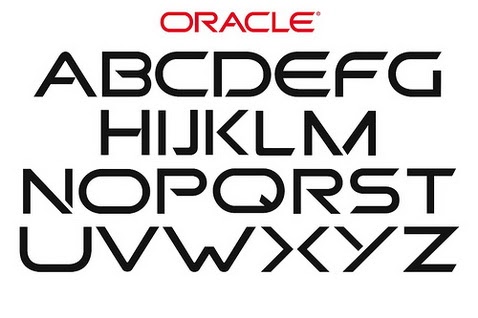
В формировании корпоративного стиля, призванного создавать образ компании, шрифт играет одну из самых заметных ролей. Он является центральным связующим элементом, упрощает и поддерживает использование логотипа, сетки и установленных правил оформления документов. Характерная форма букв шрифта фиксируется в подсознании и формирует уникальный образ компании. Шрифт, особенно эксклюзивный, может служить своеобразной «скрытой рекламой» продукции вашей компании: он приводит к устойчивым ассоциациям, так же, как секундные отрывки ярких рекламных видеороликов. Есть классические шрифты, подходящие для рекламы дорогих украшений, консервативные, на которые обратят внимание приверженцы традиций, демократичные шрифты, наиболее пригодные для рекламы молодежных и детских товаров, и национальные, призванные подчеркнуть народные традиции. Профессионально спроектированные шрифты хорошо работают во всех средах коммуникации от часов до билбордов. Еще одна функция шрифта — помощь в общении с вашими партнерами по бизнесу.
Предустановленные в приложениях компании Microsoft шрифты Arial и Times New Roman стали фактически стандартом современной коммуникации. С одной стороны это упростило перенос документов с одного устройства на другое, с другой — привело к обезличиванию текстов. Чтобы вас заметили на сегодняшнем конкурентном рынке подбор правильного шрифта не менее важен, чем создание логотипа.
Успешность коммуникации бренда с потребителем определяется его присутствием во всем многообразии медийных сред от рекламных щитов на магистралях до мобильных приложений на часах клиента. Непрерывность взаимодействия с потребителем — основа развития в этом быстро меняющемся мире.
Клиенты, особенно молодые, технологически грамотные, ожидают увидеть ваш бренд на нескольких платформах, что позволяет легко взаимодействовать с ним по своему усмотрению. По данным Google, 65 процентов потребителей начинают онлайн-операции на одном устройстве, а продолжают на другом. Сегодня текст и шрифт более важны для бренда, чем когда-либо, а использование последовательной типографии становится основным и самым простым способом установить ту самую непрерывность.
Леттеринг — это создание уникальной надписи, в которой каждая буква чаще всего создается в несколько приемов и с использованием нескольких инструментов. Неоновая вывеска, меню на грифельной доске ресторана или вылепленные годы постройки здания на фасаде — все это леттеринг. Задача леттеринга передать красоту каждой буквы и надписи в целом. Уникальность использования позволяет дизайнеру очень точно использовать контекст, в котором надпись будет работать, подобрать необходимые инструменты и форму выражения.
Сегодня дизайн логотипа — это маленькая подгруппа брендинга, которая в наши дни может включать в себя огромное количество направлений, от дизайна интерьера до позиционирования в социальных сетях, но логотип остается центральным элементом большинства брендинговых схем. Это образ, с которым люди сразу свяжут ваш бренд, который вызовет эмоции, связанные с опытом использования ваших продуктов. И от качества его исполнения во многом зависит будут ли они положительными или отрицательными.
Как выбрать шрифт для логотипа
Выбор шрифта для логотипа — мега-ответственная задача. И дело даже не в его красоте и оригинальности. Каждая шрифтовая гарнитура имеет свой характер, передает определенное настроение.
Сравните, как выглядит одна и та же надпись, сделанная шрифтами Impact, Chocogirl и Brusher.
Что лучше для солидной финансовой компании? Конечно, строгий, лаконичный, хорошо читабельный Impact. А вот, например, для кондитерской или какой-нибудь творческой мастерской больше подходит легкий, игривый и элегантный Chocogirl. А Brusher можно использовать, скажем, для бренда детской одежды или игрушек.
Главное правило: шрифт отражает основной месседж бренда. От внешнего вида вывески или визитки зависит, какой впечатление произведет компания.
И здесь важно учитывать все: специфику товаров и услуг, возраст и пол целевой аудитории. Согласитесь, было бы нелепо появиться на серьезном собеседовании в гламурном коктейльном платье или заявиться на пляжную вечеринку в деловом костюме!
Если в логотипе используется два или три вида шрифтов, здесь нужно быть особо внимательным! Они должны находиться в гармонии. Один — доминирует, второй — подчеркивает и дополняет. Эти шрифты не должны быть похожими друг на друга, но при этом сочетаться, иметь какие-то общие черты. Задача не из легких!
Основные типы шрифтов
Шрифты с засечками
Имеют маленькие черточки в конце основного штриха каждой буквы. Текст, написанный такими шрифтами, воспринимаются более традиционным, надежным, солидным и серьезным. Есть и минусы: тонкие черточки плохо воспринимаются на экранах компьютеров и мобильных устройств, они слабо пропечатываются на визитках, особенно мелким шрифтом.
Представьте, что вы используете жирный жирный шрифт в своем логотипе и печатаете его на фирменном бланке. Когда он напечатан на бумаге, он не будет выглядеть так хорошо и отчетливо. Так что при выборе шрифта хорошенько подумайте, как и где будет использоваться логотип.